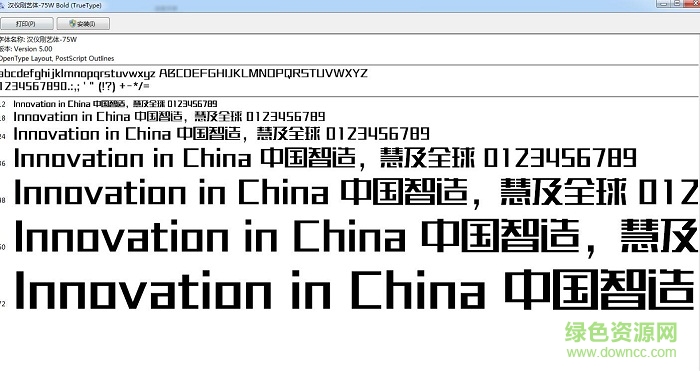
漢儀剛藝體 75w bold字體是一款簡(jiǎn)約時(shí)尚的漢儀字體,該字體筆畫強(qiáng)硬,穩(wěn)重有力,現(xiàn)代感十足,書籍封面、商業(yè)標(biāo)志設(shè)計(jì)、游戲設(shè)計(jì)等方面都可以使用,非常醒目,歡迎大家免費(fèi)下載!
【穩(wěn)重挺拔】
字體造型規(guī)整,富于力度,給人以簡(jiǎn)潔爽朗的現(xiàn)代感,有較強(qiáng)的視覺沖擊力,這種個(gè)性的字體,適合于機(jī)械科技等主題。